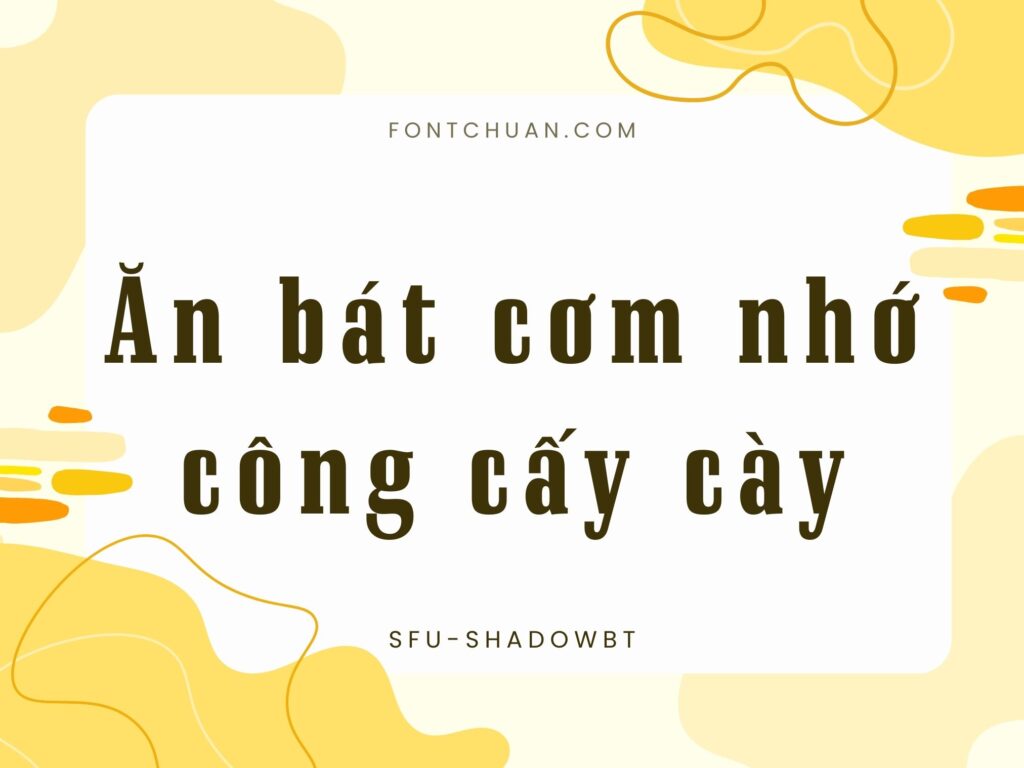
Font SFU Schadowbt Việt Hóa
Font SFU Schadow BT Black Condensed là một kiểu chữ serif đậm nét và cô đọng, được thiết kế với các đường nét mạnh mẽ và rõ ràng, tạo cảm giác cổ điển và chuyên nghiệp. Font này thích hợp cho nhiều mục đích sử dụng khác nhau, từ tiêu đề đến thiết kế đồ họa.
SFU Schadow BT Black Condensed lý tưởng cho các dự án thiết kế logo, tiêu đề, bao bì sản phẩm và các ấn phẩm quảng cáo. Các ngành nghề như quảng cáo, giáo dục và công nghệ có thể tận dụng font này để tạo điểm nhấn trong thiết kế. Ngoài ra, font cũng thích hợp cho các sự kiện như Tết, Giáng sinh, Valentine và các lễ hội khác.